Top 15 font chữ cho menu nhà hàng chay, thực dưỡng và thương hiệu xanh
Gợi ý 15 font TH Việt hóa phù hợp cho menu nhà hàng chay, thương hiệu thực dưỡng, organic food và nhận diện xanh: mộc mạc, dễ đọc, tinh tế.
Menu nhà hàng chay không chỉ cần đẹp. Nó cần tạo cảm giác sạch, an tâm, tự nhiên và dễ chọn món. Một kiểu chữ quá vui có thể làm thương hiệu bị trẻ con; một kiểu chữ quá sang lại dễ xa cách; còn font quá cầu kỳ sẽ khiến khách đọc chậm, nhất là khi menu có nhiều món, nhiều thành phần và nhiều mức giá.
Với nhóm thiết kế cho quán chay, thực dưỡng, vegan, organic food hoặc thương hiệu xanh, font nên đi theo ba hướng chính: mộc mạc để gợi cảm giác thủ công, thanh lịch để nâng chất lượng thương hiệu, và rõ ràng để khách đọc tên món nhanh. Bài viết này chọn 15 font TH Việt hóa trên Fontdep.vn, ưu tiên những font có thể dùng cho tiếng Việt đầy đủ, hợp với bảng menu, poster món theo mùa, bao bì đồ ăn lành mạnh, logo quán chay và social post.
Chọn font menu nhà hàng chay cần chú ý điều gì?
Với menu chay và thực dưỡng, cảm giác “tự nhiên” quan trọng nhưng chưa đủ. Font phải giúp khách nhận ra nhóm món, đọc đúng tên món tiếng Việt và hiểu nhanh mức giá. Nếu menu có nhiều món từ đậu, nấm, rau củ, hạt, trà, nước ép hoặc món theo mùa, anh nên dùng font trang trí cho tiêu đề và dùng font rõ ràng cho mô tả.
Nhóm font hoài cổ hợp với quán chay gia đình, cơm chay Việt, menu giấy kraft và không gian có vật liệu gỗ, tre, gốm. Nhóm serif thanh lịch hợp với nhà hàng chay cao cấp, retreat, wellness, khách sạn, spa hoặc thương hiệu organic cần độ tin cậy. Nhóm viết tay chỉ nên làm điểm nhấn cho lời nhắn, slogan hoặc nhãn phụ để tránh rối mắt.
Top 15 font TH cho menu nhà hàng chay, thực dưỡng và thương hiệu xanh
1. TH HC Calvous - menu quán chay phong cách cơm nhà, bảng món theo ngày và poster món Việt mộc mạc
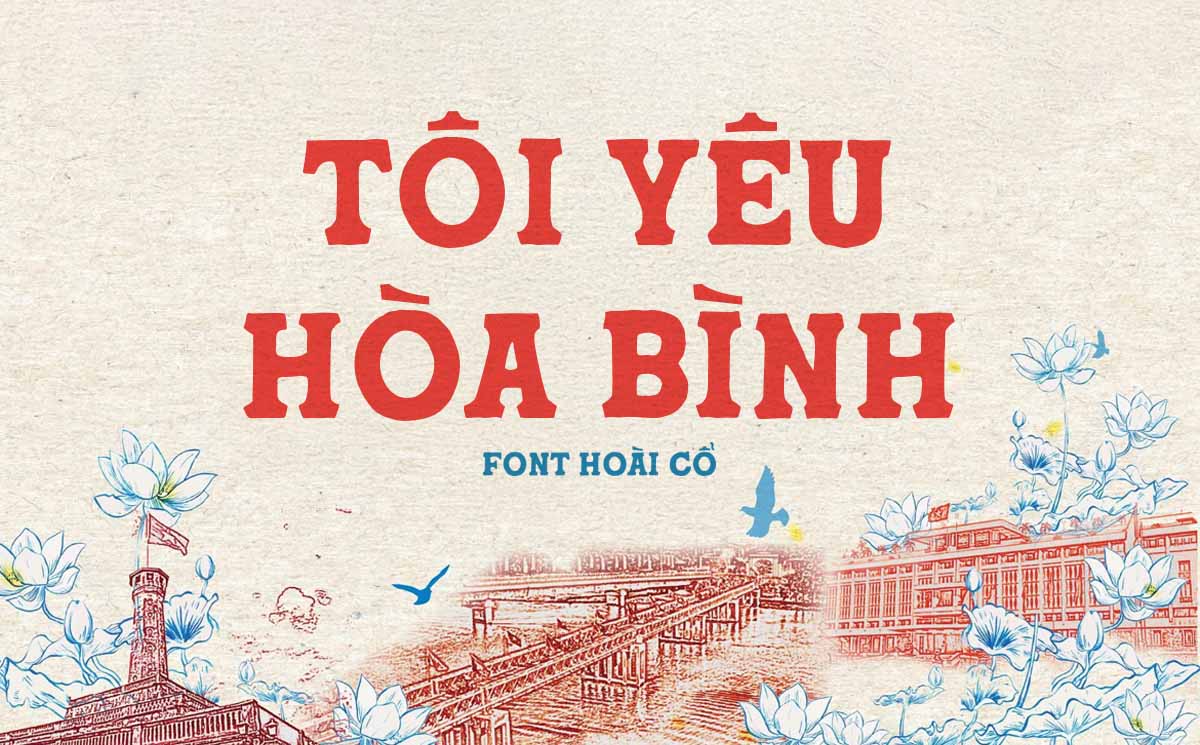
Tải font TH HC Calvous nếu anh đang làm menu quán chay phong cách cơm nhà, bảng món theo ngày và poster món Việt mộc mạc. TH HC Calvous phù hợp với menu quán chay phong cách cơm nhà, bảng món theo ngày và poster món Việt mộc mạc. Khi dùng cho menu nhà hàng chay, font này nên đặt ở tiêu đề món, tên nhóm món hoặc headline ngắn thay vì dùng cho toàn bộ mô tả nguyên liệu.
Điểm đáng dùng của TH HC Calvous là tạo được cá tính riêng mà vẫn giữ tinh thần gần gũi. Hãy thử font với các cụm như “cơm gạo lứt”, “rau củ hấp”, “nấm kho tiêu”, “set thanh lọc” hoặc “món theo mùa” trên nền giấy kraft, trắng ngà, xanh olive nhạt để kiểm tra độ sạch và độ đọc. Khi phối font, hãy để TH HC Calvous làm giọng chính ở vùng cần nhớ, sau đó ghép cùng một sans-serif đơn giản cho giá, khẩu phần, ghi chú dị ứng và thành phần.
2. TH Colombo Sans - bảng menu rõ ràng, poster combo chay và nhận diện quán ăn xanh cần chất xưa vừa phải
Tải font TH Colombo Sans nếu anh đang làm bảng menu rõ ràng, poster combo chay và nhận diện quán ăn xanh cần chất xưa vừa phải. TH Colombo Sans phù hợp với bảng menu rõ ràng, poster combo chay và nhận diện quán ăn xanh cần chất xưa vừa phải. Khi dùng cho menu nhà hàng chay, font này nên đặt ở tiêu đề món, tên nhóm món hoặc headline ngắn thay vì dùng cho toàn bộ mô tả nguyên liệu.
Điểm đáng dùng của TH Colombo Sans là tạo được cá tính riêng mà vẫn giữ tinh thần gần gũi. Hãy thử font với các cụm như “cơm gạo lứt”, “rau củ hấp”, “nấm kho tiêu”, “set thanh lọc” hoặc “món theo mùa” trên nền giấy kraft, trắng ngà, xanh olive nhạt để kiểm tra độ sạch và độ đọc. Khi phối font, hãy để TH Colombo Sans làm giọng chính ở vùng cần nhớ, sau đó ghép cùng một sans-serif đơn giản cho giá, khẩu phần, ghi chú dị ứng và thành phần.
3. TH Hoaico 2 - tiêu đề thực đơn cơm chay, bao bì đồ khô, nhãn sản phẩm thủ công và bộ nhận diện hoài niệm
Tải font TH Hoaico 2 nếu anh đang làm tiêu đề thực đơn cơm chay, bao bì đồ khô, nhãn sản phẩm thủ công và bộ nhận diện hoài niệm. TH Hoaico 2 phù hợp với tiêu đề thực đơn cơm chay, bao bì đồ khô, nhãn sản phẩm thủ công và bộ nhận diện hoài niệm. Khi dùng cho menu nhà hàng chay, font này nên đặt ở tiêu đề món, tên nhóm món hoặc headline ngắn thay vì dùng cho toàn bộ mô tả nguyên liệu.
Điểm đáng dùng của TH Hoaico 2 là tạo được cá tính riêng mà vẫn giữ tinh thần gần gũi. Hãy thử font với các cụm như “cơm gạo lứt”, “rau củ hấp”, “nấm kho tiêu”, “set thanh lọc” hoặc “món theo mùa” trên nền giấy kraft, trắng ngà, xanh olive nhạt để kiểm tra độ sạch và độ đọc. Khi phối font, hãy để TH Hoaico 2 làm giọng chính ở vùng cần nhớ, sau đó ghép cùng một sans-serif đơn giản cho giá, khẩu phần, ghi chú dị ứng và thành phần.
4. TH Hoaico 3 - menu thực dưỡng, poster món theo mùa và bảng hiệu nhỏ cần cảm giác gần gũi
Tải font TH Hoaico 3 nếu anh đang làm menu thực dưỡng, poster món theo mùa và bảng hiệu nhỏ cần cảm giác gần gũi. TH Hoaico 3 phù hợp với menu thực dưỡng, poster món theo mùa và bảng hiệu nhỏ cần cảm giác gần gũi. Khi dùng cho menu nhà hàng chay, font này nên đặt ở tiêu đề món, tên nhóm món hoặc headline ngắn thay vì dùng cho toàn bộ mô tả nguyên liệu.